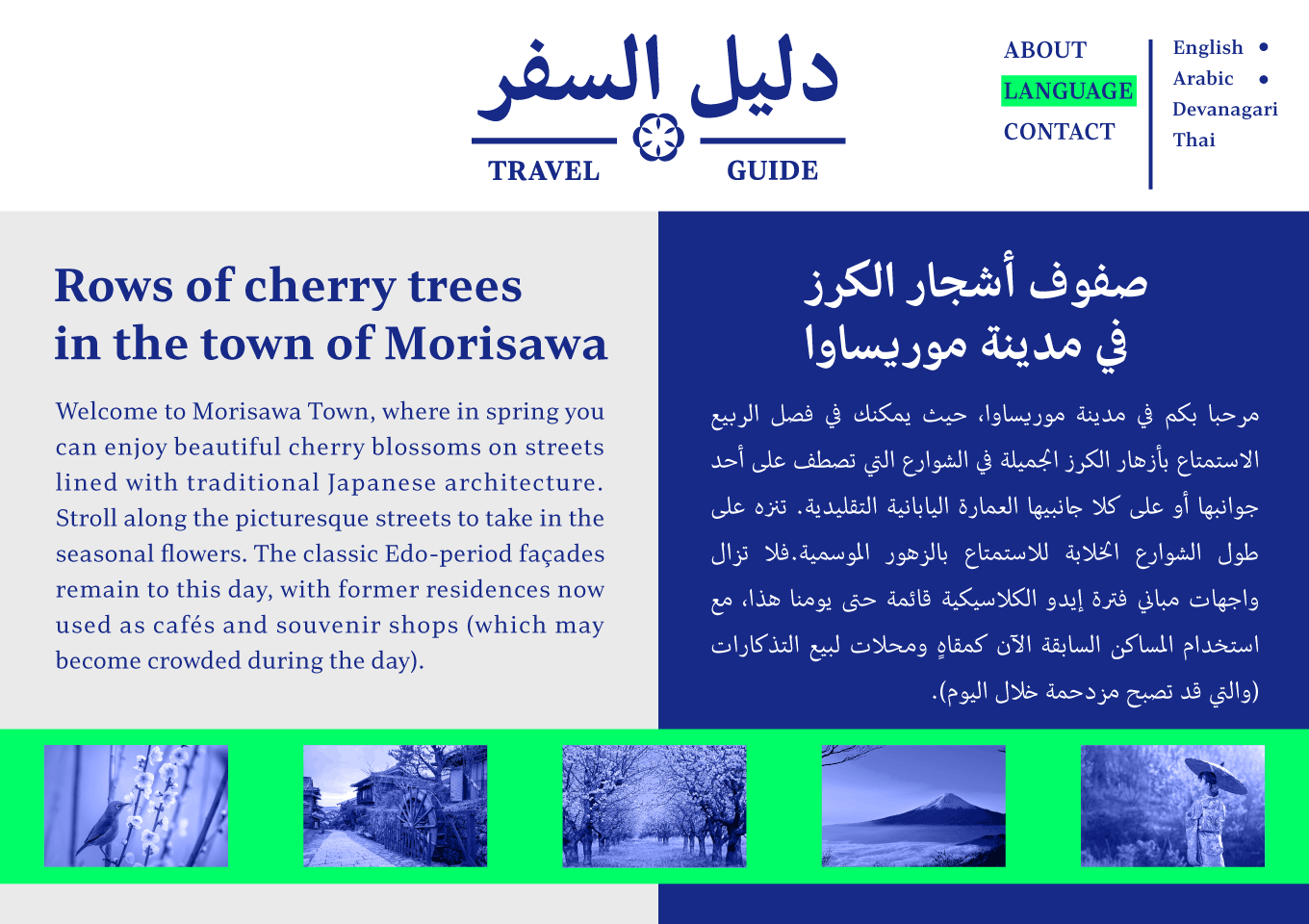
「Lutes UD Arabic」は欧文フォント 「Lutes UD PE」の多言語展開として作成されたアラビア文字のフォントです。デジタルデバイス上での視認性に配慮した、ローコントラストでありながらもクリアですっきりとした印象のセリフ書体「Lutes UD PE」の特徴を反映しています。 Lutes UD Arabicではより現地のユーザーにとって自然なデザインとなるよう、手書き由来の合字を採用しています。